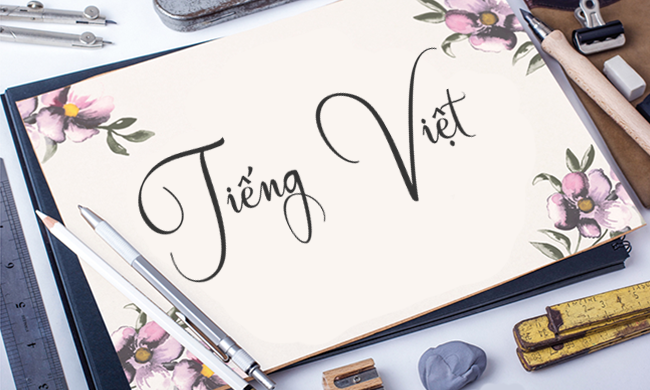
Font SVN Wallows là một phông chữ độc đáo thuộc bộ font SVN với phong cách cổ điển pha lẫn hiện đại, mang đến cảm giác mềm mại và tinh tế trong từng đường nét. Được ưa chuộng trong các dự án thiết kế như thiệp mời, tiêu đề, hoặc logo, font SVN Wallows tạo nên sự trang nhã và thanh lịch, giúp truyền tải thông điệp một cách rõ ràng và đầy ấn tượng. Với vẻ đẹp cân đối và hài hòa, phông chữ này đặc biệt phù hợp cho các thiết kế yêu cầu sự sáng tạo và tinh tế, nhưng vẫn giữ được nét sang trọng.